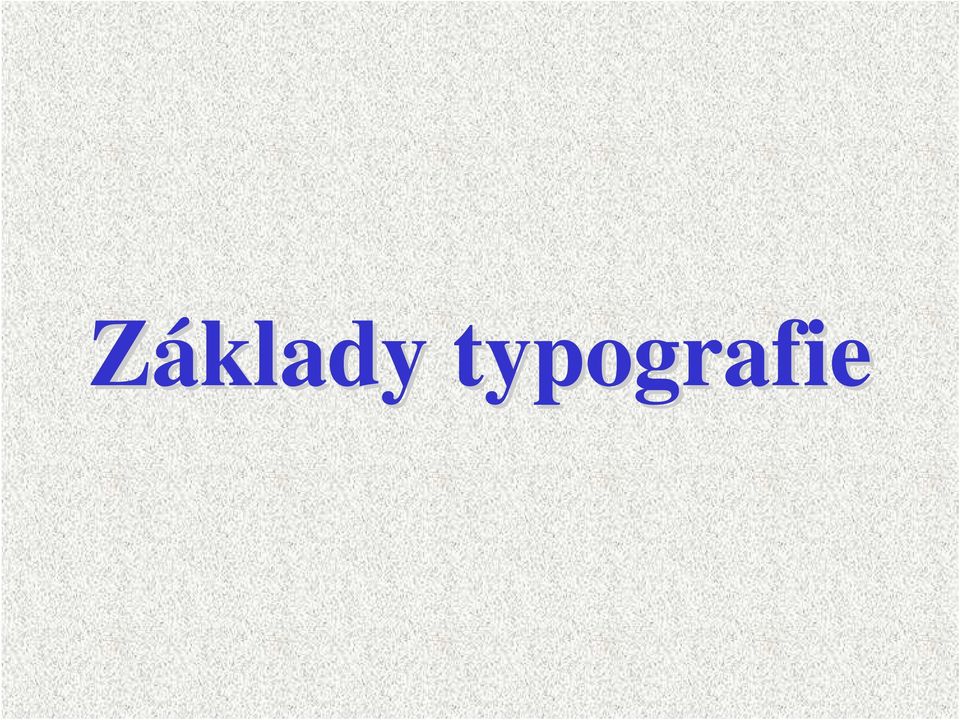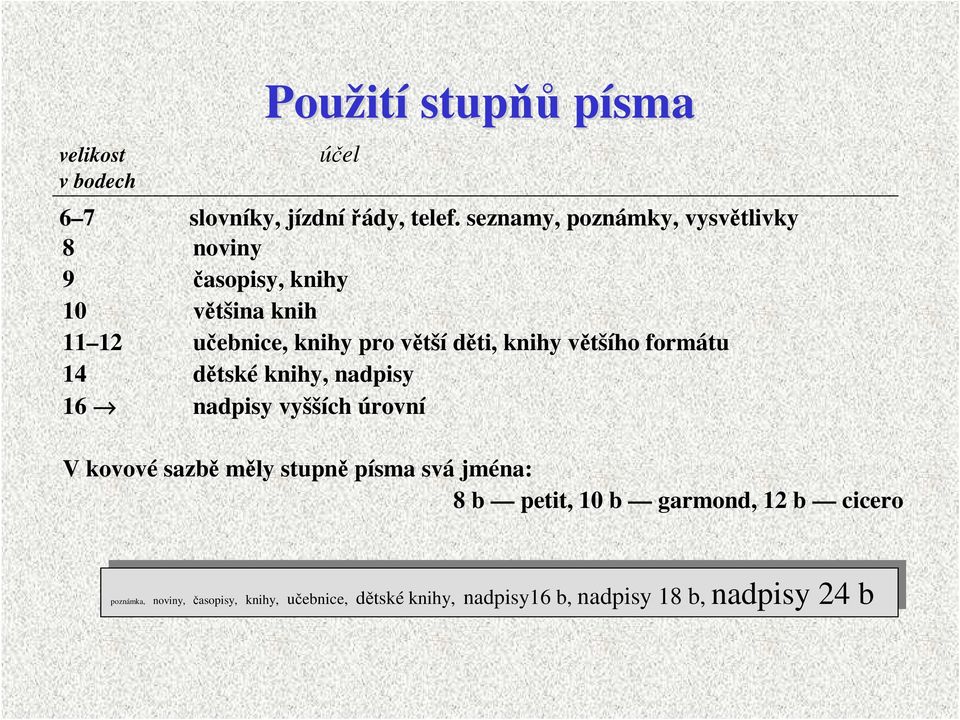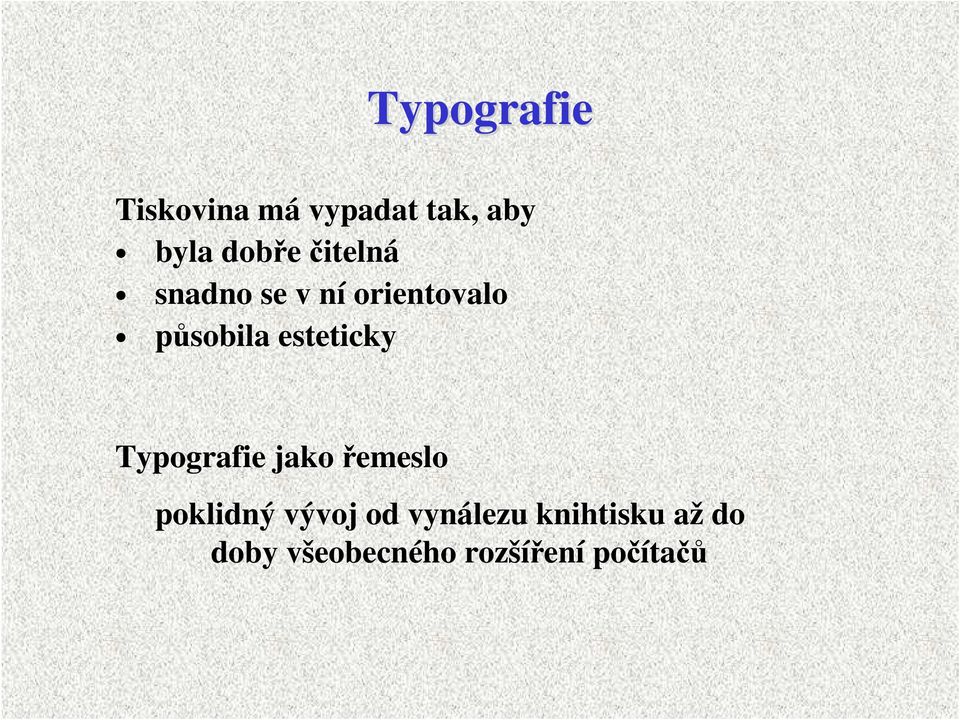
Typografie. Tiskovina má vypadat tak, aby byla dobře čitelná snadno se v ní orientovalo působila esteticky
1 Základy typografie
2 Typografie Tiskovina má vypadat tak, aby byla dobře čitelná snadno se v ní orientovalo působila esteticky Typografie jako řemeslo poklidný vývoj od vynálezu knihtisku až do doby všeobecného rozšíření počítačů
3 Motto: Podobně jako je moráln lně nepřípustn pustné veřejn ejně publikovat texty s pravopisnými chybami, je stejně nepřípustn pustné publikovat texty s vážnými v typografickými chybami.
4 Vývoj písmap důsledek vývoje civilizace (potřeby zaznamenávat) předchůdce písma piktogramy (nezávislé na jazyce) ideogramy obrazový znak splynul se slovním významem, znaky pro abstraktní pojmy a jména obrázkové písmo stovky až tisíce znaků znaky zachycují zvuky revoluce ve vývoji písma fonogramy znaky pro hlásky (dlouho jen souhlásky) vůl král
5 Nejstarší písma Klínové písmo v Mezopotámii vývoj od obrázkového písma přes slovní až po slabikové Egyptské písmo hieroglyfy hieratické písmo démonické písmo hláskové Čínské písmo (slovní písmo dodnes) slunce hora strom střed pole hranice dveře
6 Historie písma p v Evropě Fénické písmo geom. znaků pro souhlásky Řekové fénický nápis znaky pro samohlásky, psaní zleva doprava základ latinky, současného řeckého písma i azbuky Naše dnešní písmo velká z obdobíříma (stará přes 2000 let) malá z doby Karla Velikého (800) nabodeníčka (česká diakritika, Jan Hus) zlom ve vývoji vynález knihtisku (asi 1450)
7 Vývoj číslic římskéčíslice vydržely do 15 století arabskéčíslice původ v Indii MDCCLXVII 1767
8 Vlastnosti písma p soubor znaků a, b, c, malá písmena minusky (minuskule) A, B, C, velká písmena verzálky (majuskule) 1, 2, číslice ˇ diakritická znaménka akcenty (ř, š, ů, ú, akcentované znaky).,!? ; : interpunkční znaménka ( ) [ ] { } závorky uvozovky + ± = matematická znaménka % & různé další znaky
9 Vlastnosti písma p písmová osnova Písmová osnova soustava vodorovných přímek určující výškové proporce písma. akcentová dotažnice horní dotažnice verzálková dotažnice střední dotažnice základní dotažnice (účaří) dolní dotažnice
10 Vlastnosti písma p kresba písmovp smového znaku dřík hlavní tah serif (patka) příčné ukončení tahu stínování tahů duktus síla tahu hlavní tah dřík přetah nestínovaný tah patka stínovaný tah osa stínu šikmá stínovaný tah osa stínu kolmá
11 Typy písma p I. Typy písma rozlišujeme podle kresby znaku. Každý typ písma má svoje jméno. Charakteristické znaky pro rozlišení: způsob zakončení tahu (má/nemá patku) A A A A proporční neproporční A A A A má-li patku, její přechod na hlavní tah (oblý/ostrý) stínovaný/nestínovaný tah síla tahů (duktus) proporce písma - šířkové - výškové A A A A A A A A
12 Typy písma p II. Řez písmap je varianta písma, která se svou kresbou liší od základního písma. Má s ním společnou písmovou osnovu, výškové proporce a základní kresebné znaky. Rodina písmap všechny řezy jednoho typu písma. Základnířezy: základní (roman, regular) tučné (polotučné, velmi tučné) kurzíva tučná kurzíva (polotučná) kapitálky Times New Roman TIMES NEW ROMAN
13 Klasifikace písemp Antikva patkové se stínovanými tahy dynamická nejběžnější knižní písmo přechodová statická Lineární bezpatkové písmo pro nadpisy a nápisy Lineární patkové písmo Psaná písma Zdobená písma Milá maminko, píšu Ti psaníčko
14 Typografické míry 0,9385 evropský typografický měrný systém Didotův 1 bod = 0,3759 mm (zkratka b) 12 bodů = 1 cicero = 4,513 mm anglo americký typografický měrný systém 1 point = 0,3528 mm (zkratka pt) 12 points = 1 pica = 4,23 mm 72 points = 6 picas = 1 inch = 2,54 cm 1, points 54 bodů
15 Stupeň písma (velikost písma) p Stupeň písma = rozměr horní plochy na kovové liteře (kuželce) Výška písmen závisí na typu písma 60 bodů 60 bodů
16 velikost v bodech Použit ití stupňů písma účel 6 7 slovníky, jízdnířády, telef. seznamy, poznámky, vysvětlivky 8 noviny 9 časopisy, knihy 10 většina knih učebnice, knihy pro větší děti, knihy většího formátu 14 dětské knihy, nadpisy 16 nadpisy vyšších úrovní V kovové sazbě měly stupně písma svá jména: 8 b petit, 10 b garmond, 12 b cicero poznámka, noviny, časopisy, knihy, učebnice, dětské knihy, nadpisy16 b, nadpisy 18 b, 24 noviny, časopisy, knihy, učebnice, dětské knihy, nadpisy16 b, nadpisy 18 b, nadpisy 24 b
17 Relativní typografické míry Vztažené ke stupni písma em = čtverčík = stupeň písma en = 1/2 em určují se jimi šířky písmen velikosti mezislovních mezer 18 jednotek 9 jednotek 6 jedn.
18 Sazba mezery mezery mezi písmeny jsou dány šířkou znaku (kuželky) v počítačové sazbě je lze snadno upravit prostrkávání úprava mezer, někdy se užívá k zvýraznění kerning přizpůsobení mezery konkrétní dvojici znaků, dělá se jen pro velká písmena (min. 16 pt) mezery mezi slovy vhodná je mezera velikosti 1 / 3 em bývá určena minimální ( 1 / 4 em) a maximální ( 1 / 2 em) mezera pevná mezera (nezlomitelná, tvrdá) zákaz zlomu řádku J. A. Komenský 37 Kč z lesa AV MN TRÁVA